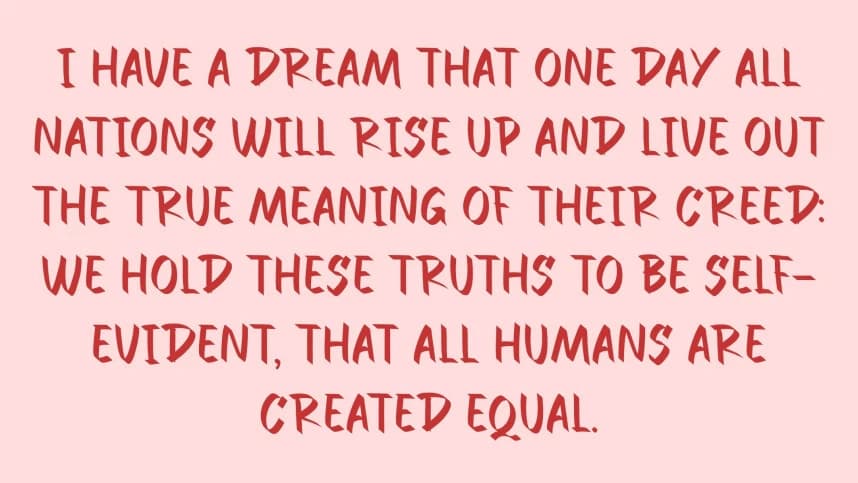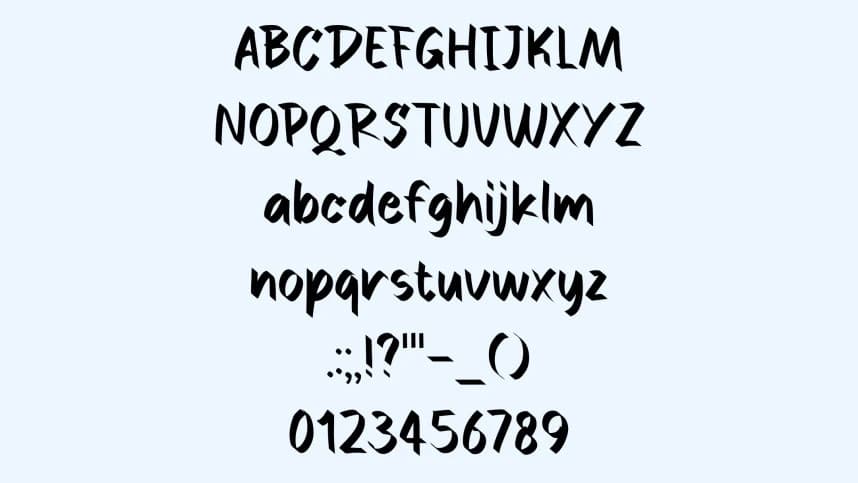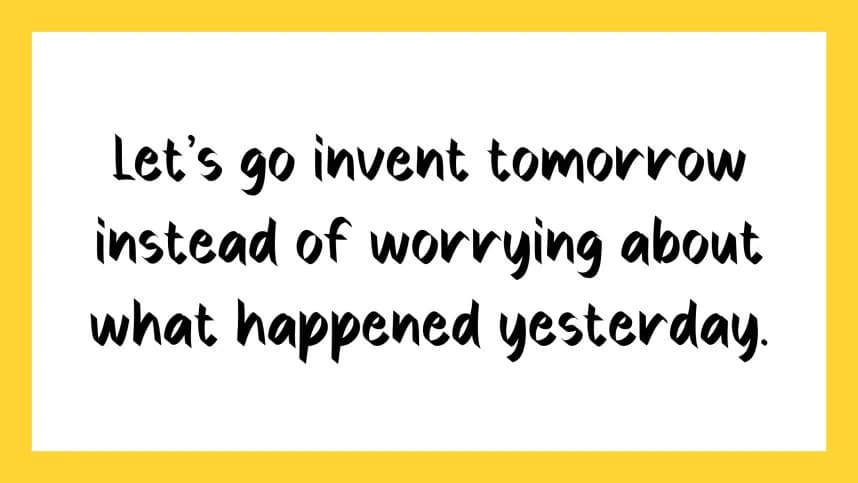
Morder Brush Font
Morder Brush Font, doğal el boyamalı fırça darbeleri ve dinamik bir el yazısı stiline sahip cesur ve ifade dolu bir fırçalı gösteri tipi yazı tipidir. Pürüzlü fırça dokusu ve enerjik harf biçimleri, otantik ve sanatsal bir görünüm yaratır.
Morder Brush Font, doğal el boyama darbelerini ve dinamik el yazısı stilini öne çıkaran cesur ve ifade dolu bir fırça gösterim yazı tipi. Kaba fırça dokusu ve enerjik harf biçimleri özgün ve sanatsal bir görünüm yaratır.